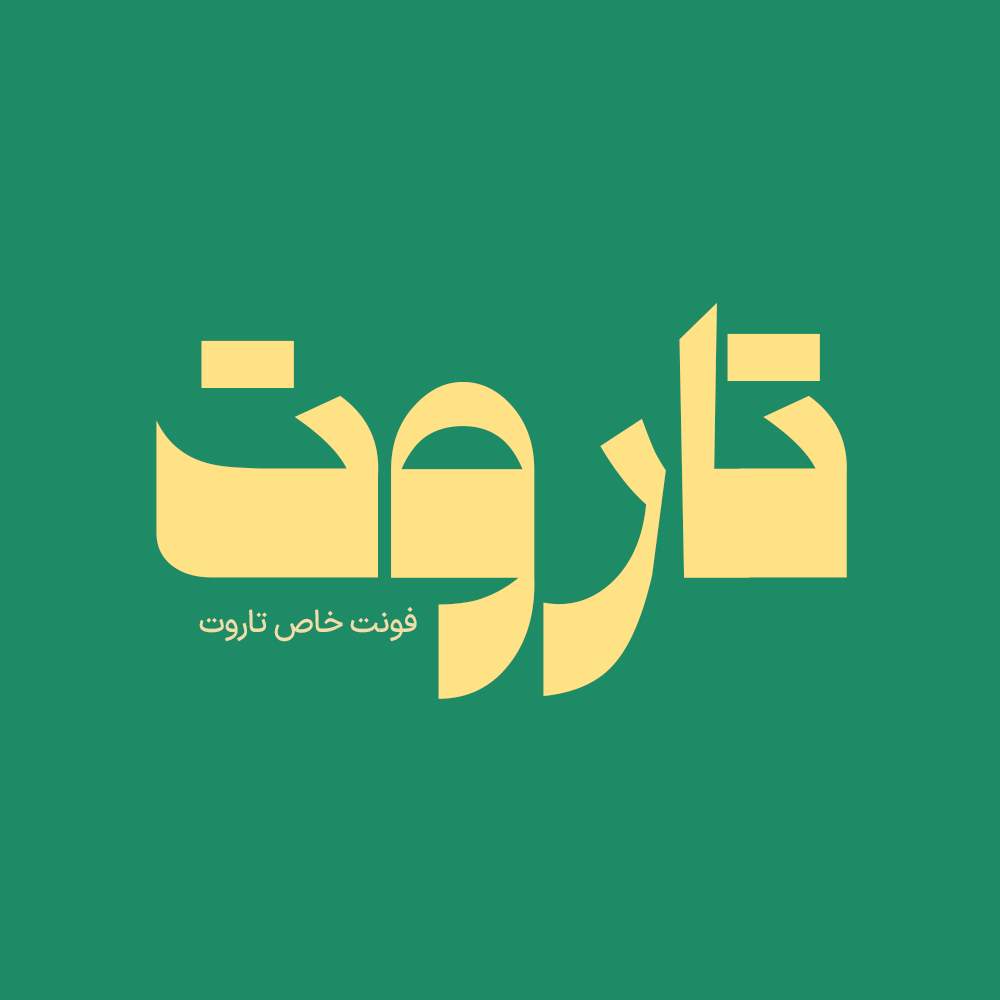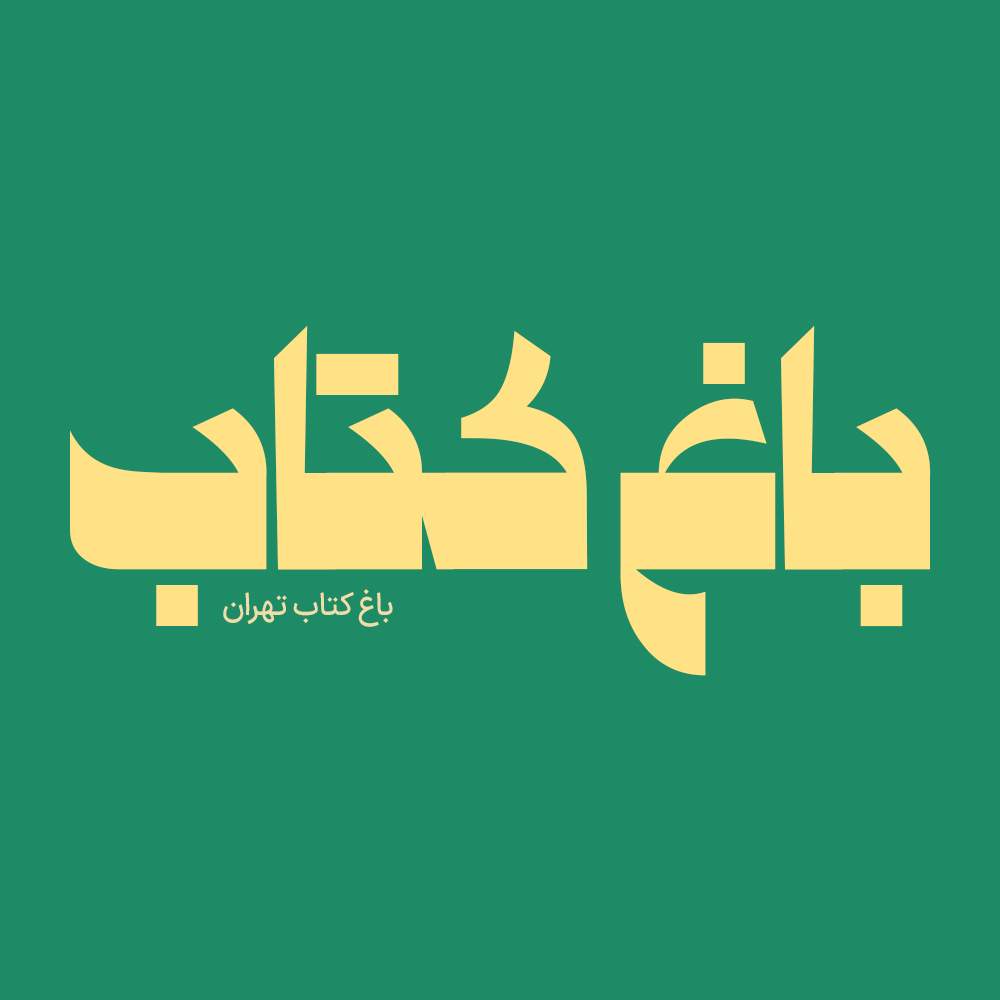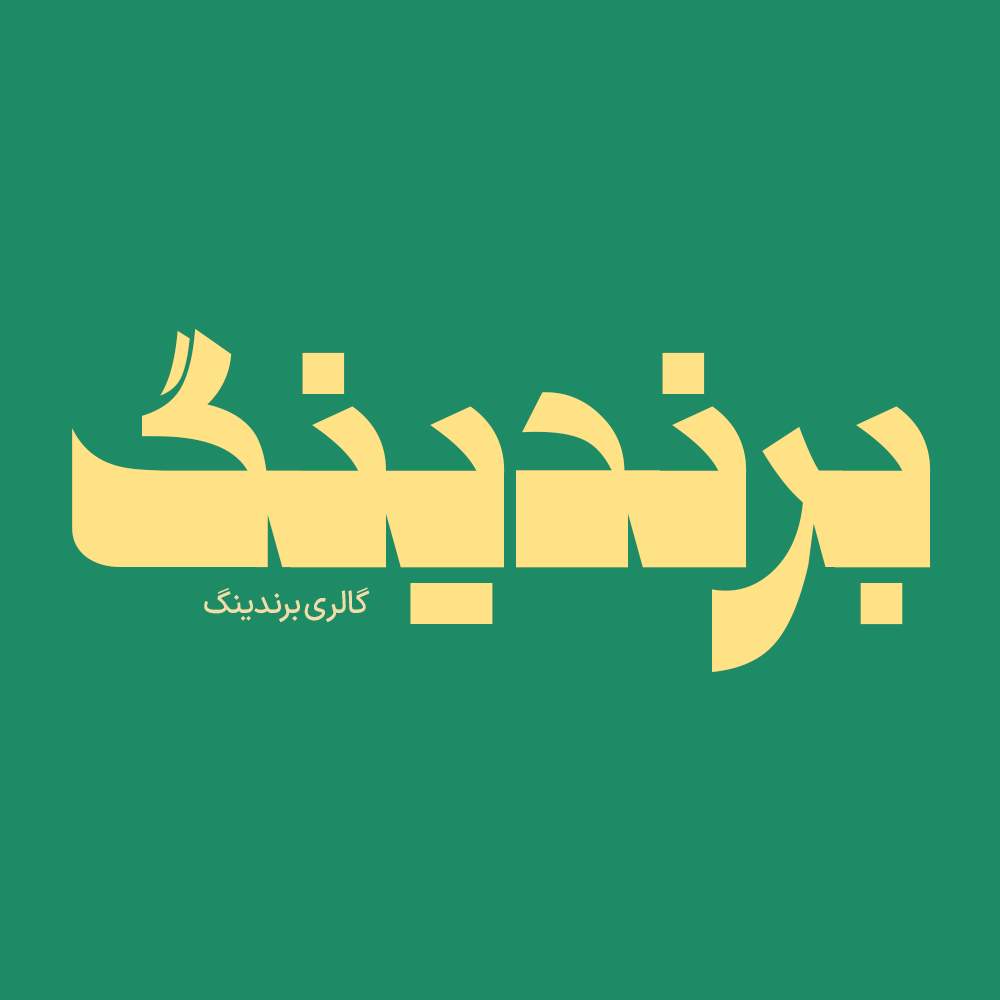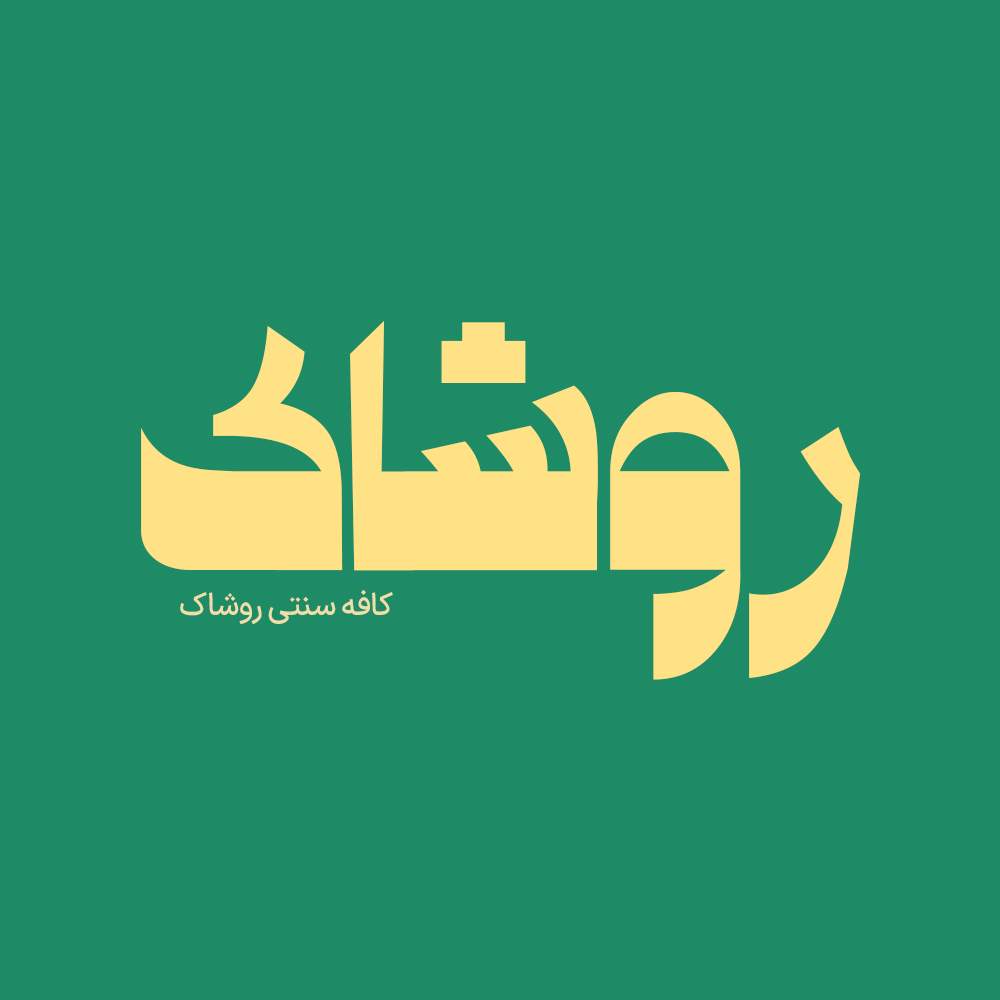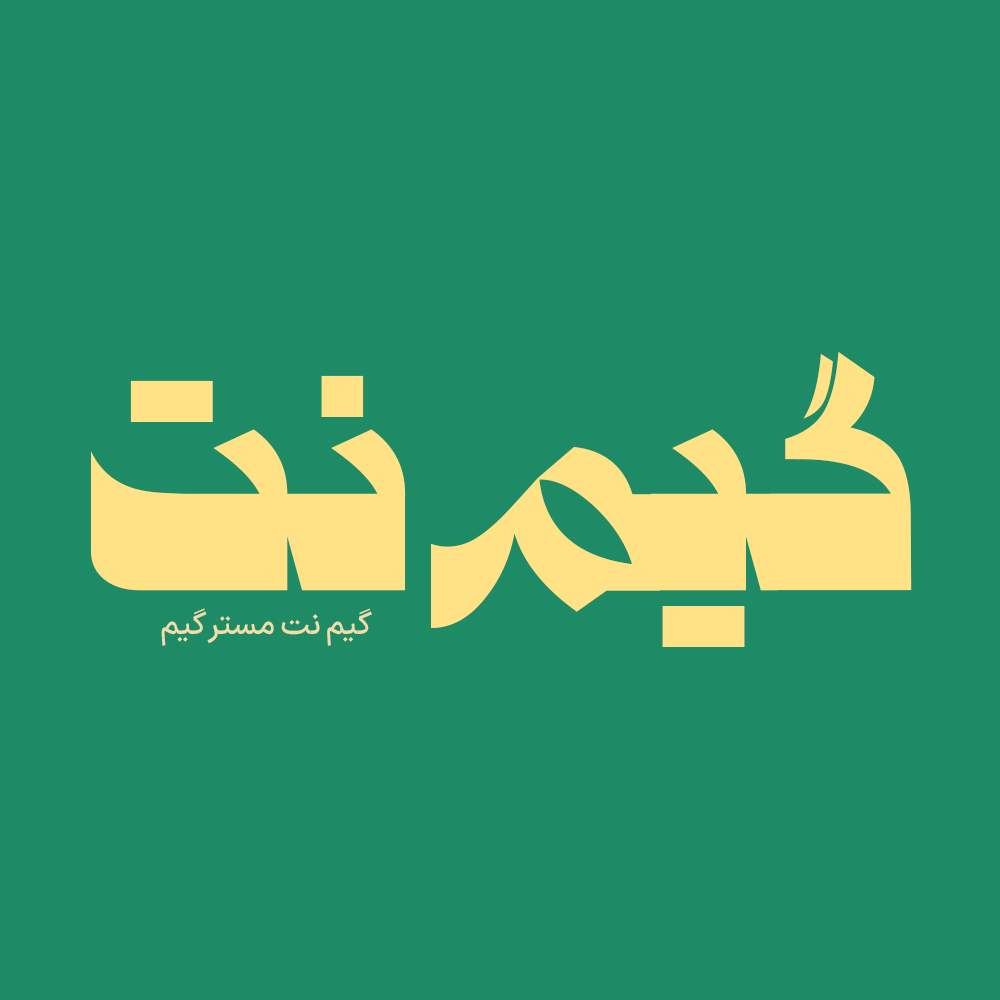
فونت فارسی تاروت Tarot Font
فونت فارسی تاروت یک فونت متفاوت و زیبای فارسی میباشد که در وزن بولد طراحی شده است، این فونت زیبا در عین سادگی که فونت های…
فونت فارسی تاروت یک فونت متفاوت و زیبای فارسی میباشد که در وزن بولد طراحی شده است، این فونت زیبا در عین سادگی که فونت های سنگین دارند یک طراحی خاص دارد که سبب متفاوت شدن و هنری تر شدن این فونت میشود و مناسب انواع طراحی گرافیکی می باشد.
فونت تاروت یک فونت تک وزن با کاربرد طراحی لوگوتایپ و طراحیهای مختلف همچون کتاب و تولید محتوای متنهای کوتاه و عناوین میباشد. این فونت با ساختار حروف خود مناسب استفاده در لوگوهای نوشتاری میباشد. همچنین از این فونت در طراحی تابلوهای چلنیوم هم به دلیل ساختار منحصر به فردش میتوانید استفاده کنید. در ادامه برای شما نمونه تایپ های این محصول حرفهای رو آماده کردهایم که میتوانید مشاهده کنید.